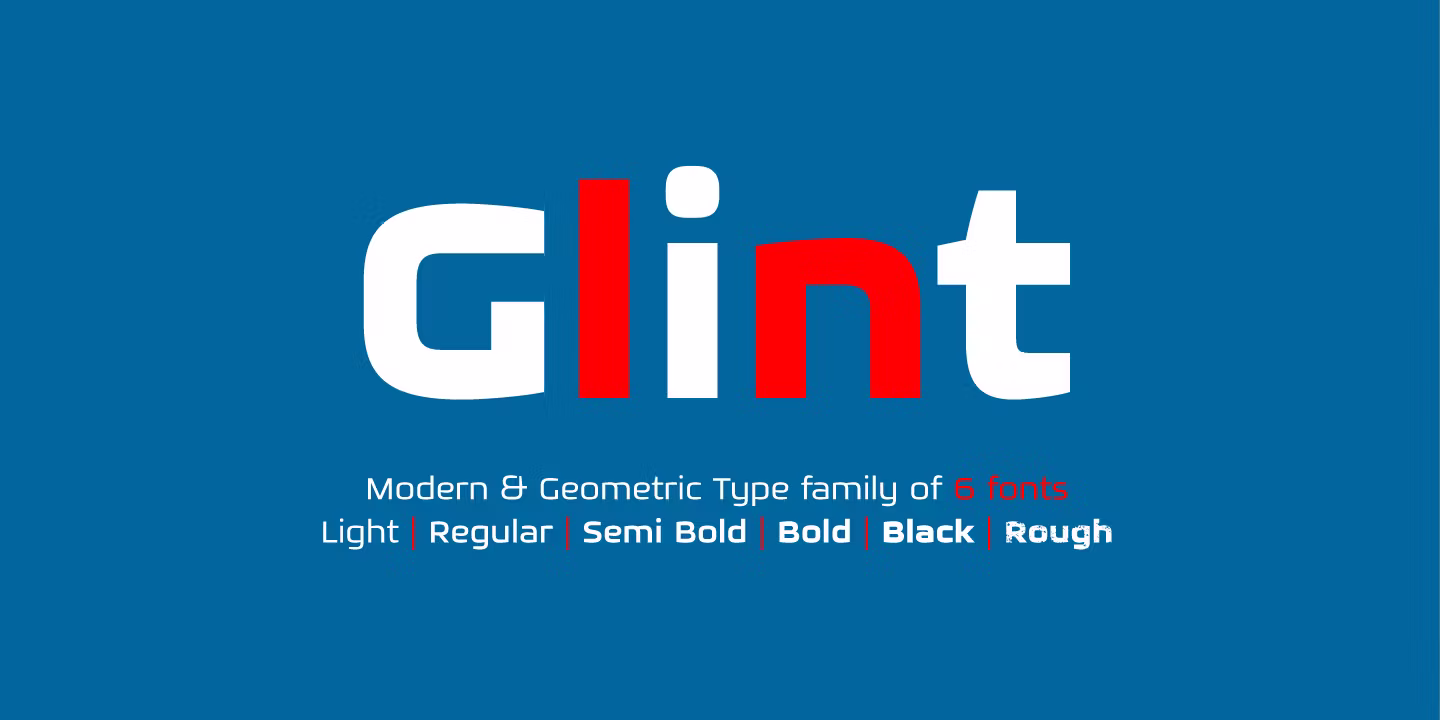
Nhiều người gặp lỗi khi sử dụng font Glint do thiếu dấu tiếng Việt hoặc đường nét chữ bị vỡ khi phóng lớn để in trên hộp quà công nghệ. Những lỗi hiển thị này có thể làm giảm tính đồng nhất của thiết kế, ảnh hưởng đến sự chuyên nghiệp của bộ nhận diện thương hiệu khi đưa vào sản xuất.
Font Glint là gì?
Font Glint là một bộ phông chữ thuộc dòng Sans-serif hiện đại, gây ấn tượng nhờ cấu trúc hình học tối giản và các đường vát góc tinh tế. Đây là loại phông chữ mang tinh thần sáng tạo, gợi lên sự chuyển động và tốc độ, phù hợp cho các thiết kế logo công ty công nghệ, ô tô, điện tử hoặc bao bì thực phẩm chức năng. Glint mang lại vẻ ngoài lịch lãm, hiện đại và chuyên nghiệp cho mọi ấn phẩm truyền thông.
Điểm mạnh của Glint là khả năng nhận diện trên nhiều bề mặt chất liệu khác nhau. Bản Font glint Việt hóa tại In Viva đã được hiệu chỉnh bảng mã Unicode chuẩn, giúp designer gõ tiếng Việt ổn định mà không làm mất đi các góc vát đặc trưng của bộ chữ. Việc sử dụng phông chữ này giúp các sản phẩm in ấn quà tặng của doanh nghiệp bạn toát lên vẻ ngoài sang trọng, bắt kịp xu hướng thiết kế tối giản.
5 ứng dụng của font Glint trong thiết kế và sản xuất
Vẻ đẹp hiện đại và mạnh mẽ của Glint giúp các sản phẩm bao bì, quà tặng doanh nghiệp trở nên chuyên nghiệp hơn khi kết hợp cùng các kỹ thuật in ấn và gia công phù hợp:
• Thiết kế bao bì hộp quà công nghệ: Glint phù hợp để thể hiện tên thương hiệu, logo hoặc thông tin sản phẩm trên hộp cứng đựng sạc dự phòng, tai nghe, thiết bị điện tử. Cấu trúc chữ hiện đại giúp bao bì tạo cảm giác chuyên nghiệp và phù hợp với ngành hàng công nghệ.
• Sản xuất set quà tặng văn phòng cao cấp: Logo sử dụng font Glint khi in UV trên bình giữ nhiệt kim loại, sạc dự phòng hoặc khắc laser trên bút ký, sổ tay giúp tạo điểm nhấn tối giản, phù hợp với phong cách quà tặng dành cho doanh nghiệp.
• In ấn túi giấy thương hiệu điện máy: Sử dụng phông chữ Glint cho logo, slogan hoặc thông tin liên hệ trên túi giấy Ivory giúp bộ nhận diện thương hiệu thể hiện sự hiện đại, rõ ràng và đồng nhất.
• Trang trí bảng biển showroom: Với định dạng vector, font Glint có thể ứng dụng trong thiết kế bảng hiệu, backdrop hoặc khu vực trưng bày cần phóng lớn. Đường nét chữ được giữ rõ ràng, giúp không gian thương hiệu có sự thống nhất về hình ảnh.
• Sản xuất kỷ niệm chương và vật phẩm vinh danh: Font Glint Bold phù hợp để khắc tên doanh nghiệp, thông tin sự kiện trên pha lê, mica hoặc kim loại. Kiểu chữ rõ nét giúp sản phẩm quà tặng lưu niệm trở nên trang trọng hơn.
5 lưu ý khi sử dụng font Glint việt hóa
Để font Glint giữ được đường nét sắc sảo khi đưa vào sản xuất thực tế, designer cần chú ý các yếu tố kỹ thuật sau:
• Kiểm soát độ vát các góc chữ: Glint có nhiều chi tiết góc cạnh đặc trưng. Khi in trên các chất liệu như kim loại, mica hoặc giấy mỹ thuật, cần kiểm tra kích thước chữ để hạn chế tình trạng mất chi tiết ở các phần góc nhỏ.
• Tối ưu đường Path cho gia công dập nổi: Khi sử dụng font Glint làm logo trên hộp quà cao cấp, file vector cần được xử lý các điểm neo và đường nét góc cạnh. Việc tối ưu path giúp khuôn dập tái hiện đúng hình dạng chữ, hạn chế ảnh hưởng đến bề mặt giấy trong quá trình gia công.
• Kiểm tra hệ màu CMYK trước khi in: Với phong cách chữ hiện đại, sự thay đổi màu sắc có thể ảnh hưởng đến tổng thể thiết kế. Designer nên thiết lập đúng thông số CMYK để màu chữ sau in phù hợp với bản thiết kế ban đầu.
• Lựa chọn kích thước chữ phù hợp: Glint phù hợp với logo, tiêu đề hoặc slogan ngắn. Khi sử dụng cho nội dung dài, nên kết hợp cùng các font chữ dễ đọc hơn để bố cục thiết kế cân đối.